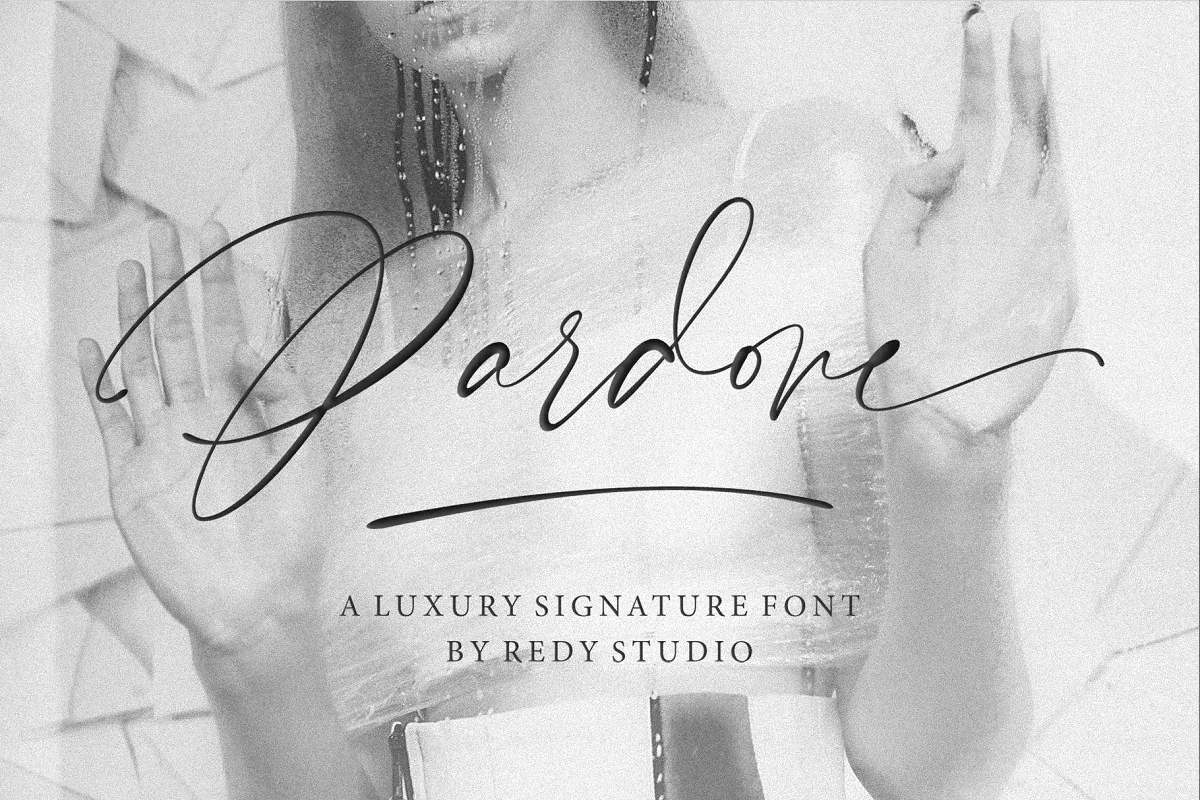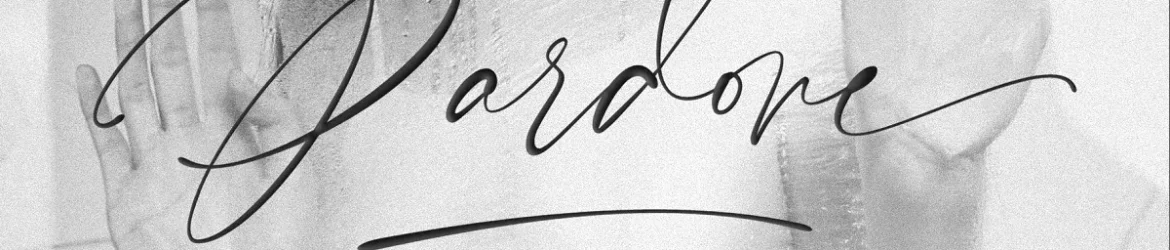
A fonte Pardone é uma escolha ideal para qualquer designer que busca adicionar um toque autêntico e moderno aos seus projetos digitais. Desenvolvida pela RedyStudio, esta fonte script apresenta uma textura única, imprimindo uma sensação de escrita à mão em cada caractere. Com Pardone, você terá acesso a toda a magnífica combinação dos caracteres maiúsculos e minúsculos, junto com um riquíssimo conjunto de números e pontuação, garantido para tornar seu projeto ainda mais profissional. Com 68 ligaturas, alternativas e fins à mão das letras minúsculas, a Pardone oferece uma ampla gama de opções. Além disso, ela também inclui sinais multilíngues que adicionam um toque cosmopolita e sofisticado ao seu design. Esses detalhes são perfeitos para criar um efeito visual único, com as alternativas à mão minúsculas e os swashes proporcionando um aspecto autêntico e atraente às suas criações. Se você busca uma fonte moderna que ainda mantém aquela sensação de escrita à mão, Pardone é definitivamente o caminho para seguir. Com sua variedade única e rica em detalhes, esta fonte script ficará perfeitamente adaptada a qualquer projeto, desde gráficos digitais até publicações online e impressas. Descubra por si mesmo o poder da Pardone na sua próxima criação!